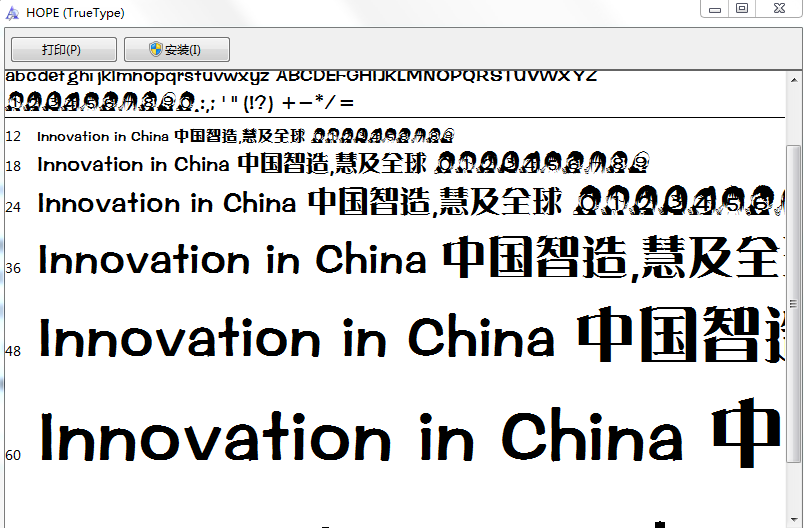
萌萌的憂(yōu)傷字體是一款比較簡(jiǎn)單的字體,支持中英文雙語(yǔ),中文比較端正,英文稍微有點(diǎn)具有卡通意味,阿拉伯?dāng)?shù)字則隱藏在憂(yōu)傷的卡通人物里面,非常的別具一格,喜愛(ài)的朋友趕快下載體驗(yàn)吧!
萌萌的憂(yōu)傷字體是一款非常個(gè)性的字體,其實(shí)從中英文字體來(lái)說(shuō),該字體還是比較端正、大氣的,而且還具有手寫(xiě)風(fēng)格。主要是數(shù)字隱藏在卡通人像中,看起來(lái)個(gè)性十足。